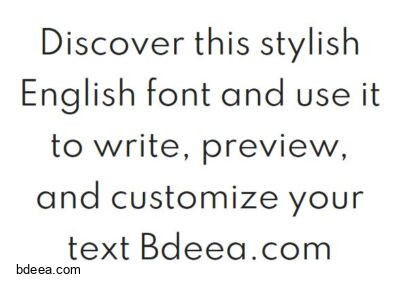
خط انجليزي سبارتن Spartan font download
حمّل خط انجليزي سبارتن Spartan font download واستمتع بمظهر أنيق وواضح للنصوص الإنجليزية في التصاميم والمستندات والمواقع. يتميز الخط بتناسق الحروف وسهولة القراءة، مما يجعله مناسبًا للعناوين والنصوص والتقارير والفواتير ومختلف الاستخدامات المكتبية والتصميمية.